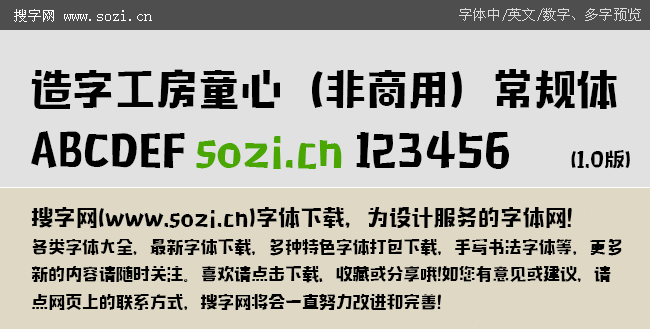
造字工房童心(非商用)常規(guī)體
搜字網(wǎng)提供一款造字工房童心(非商用)常規(guī)體中文字體下載,造字工房童心(非商用)常規(guī)體童趣盎然、個(gè)性強(qiáng)烈,字形有著濃郁詼諧可愛(ài)的氣息、其筆畫(huà)的穿插生動(dòng)、粗細(xì)形態(tài)肆意多變、欹正呼應(yīng)、給人活潑而不失穩(wěn)重之感,大氣而靈動(dòng)。口和撇的圓潤(rùn)處理讓字形更加個(gè)性鮮明,生動(dòng)有趣,有著很強(qiáng)的視覺(jué)表現(xiàn)力。適用于大標(biāo)題及個(gè)性品牌設(shè)計(jì)推廣等環(huán)境。